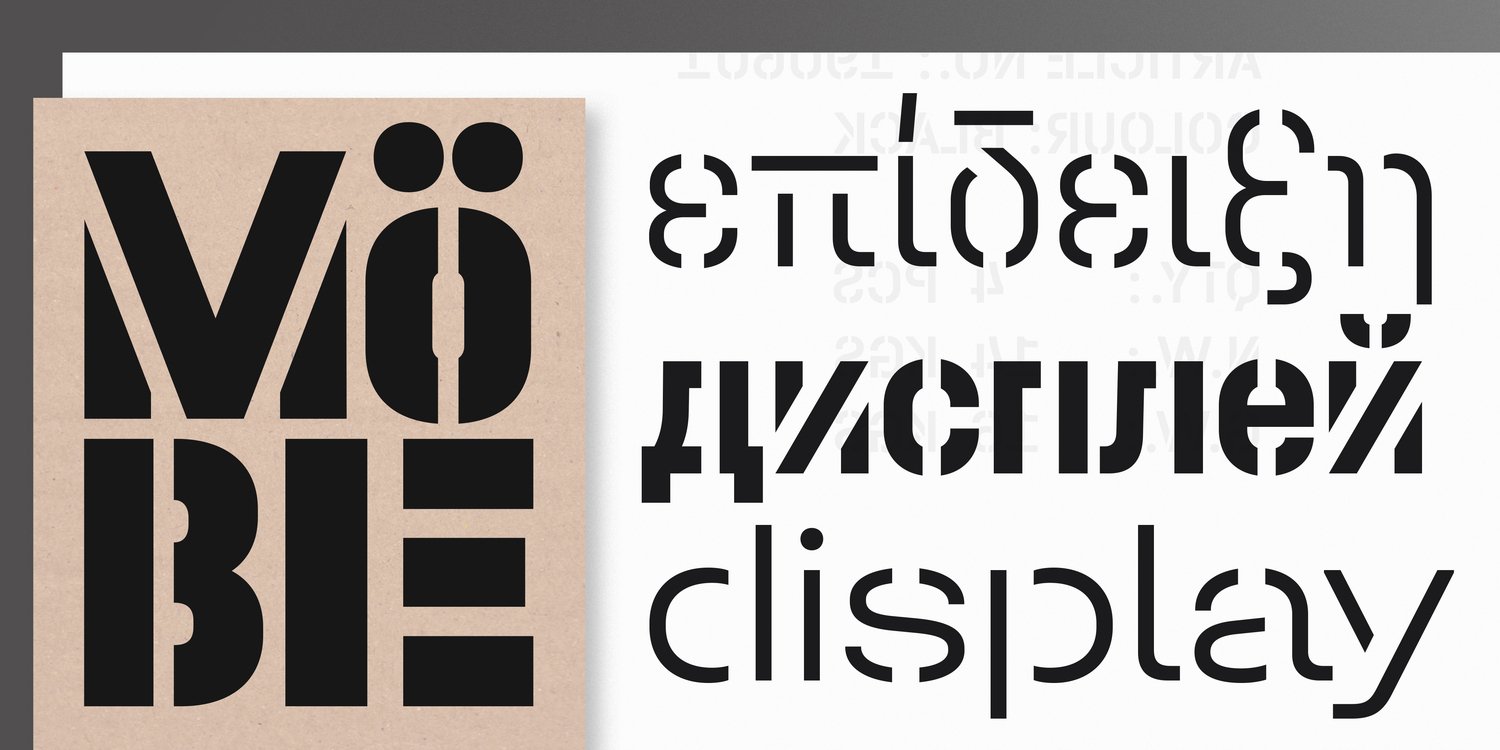
Начертания сгруппированы в три подсемейства: широкое Breitschrift, стандартное Mittelschrift и узкое Engschrift. Помимо разных насыщенностей, в шрифте есть и разные степени наклона: более широкое и выразительное Superslanted и обычное Slanted. У всех прямых начертаний Halvar (а также в начертании Slanted) единая ширина знака. Благодаря этому шрифт удобно использовать там, где ширина имеет особенное значение: например, в узких печатных колонках или в экранных интерфейсах. Halvar подходит для экрана не только поэтому: у него простой и современный силуэт, стабильная высота строчных, сделан ручной хинтинг — оптимизация контуров для отображения на экране.
В трафаретной версии Halvar ещё сильнее проявляется промышленный, инженерный дух шрифта. Halvar Stencil разработан в духе немецкого Schablonenschrift и отлично подходит для использования по прямому назначению — на стройках, на железной дороге, на электростанциях, на любых табличках с номерами. Шрифт привлекает внимание, но выглядит строгим и техническим — благодаря этому он работает и в акцидентном наборе.
Для набора в разных размерах разработано три варианта шрифта: Maxgap, Midgap и Mingap, которые различаются размером зазоров между деталями трафарета.
Так же как и в обычном Halvar, в трафаретном много вариантов насыщенности, три ширины (узкий Engschrift, средний Mittelschrift, широкий Breitschrift) и единая ширина знаков вне зависимости от насыщенности начертания. Это позволяет дизайнеру разработать гибкую и выразительную шрифтовую систему, основанную на трафаретных начертаниях, — возможно, впервые в истории кириллицы.